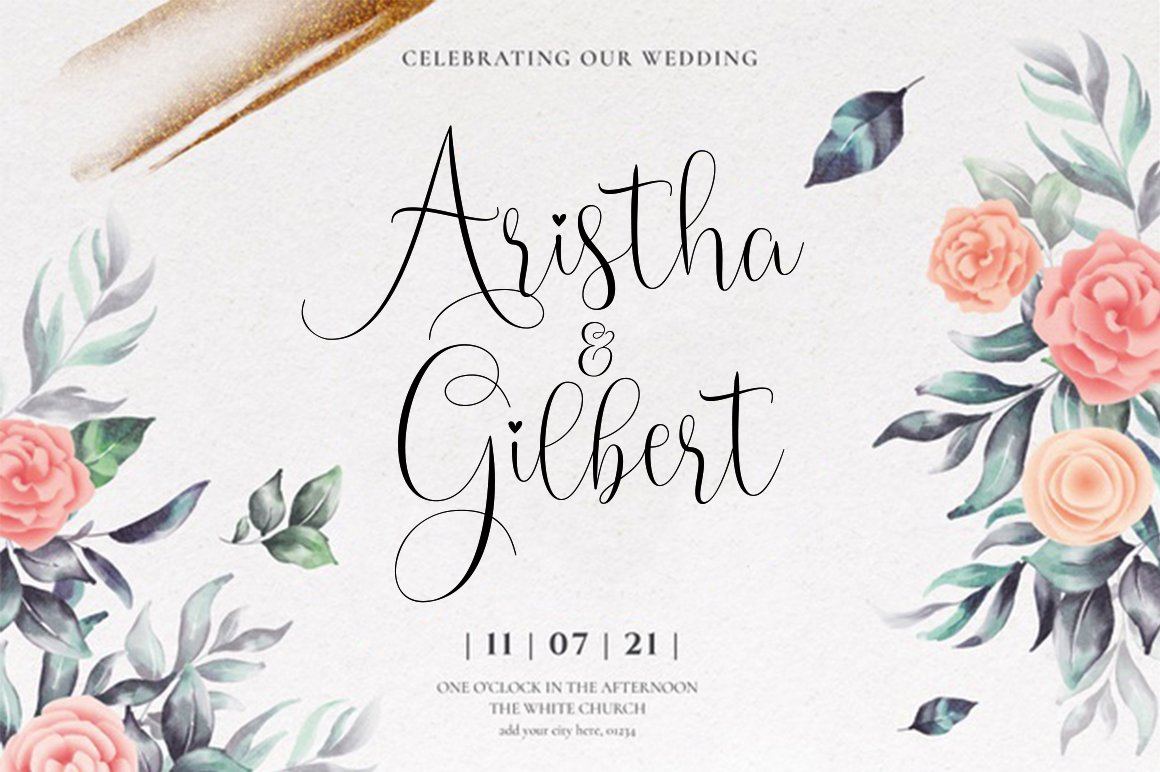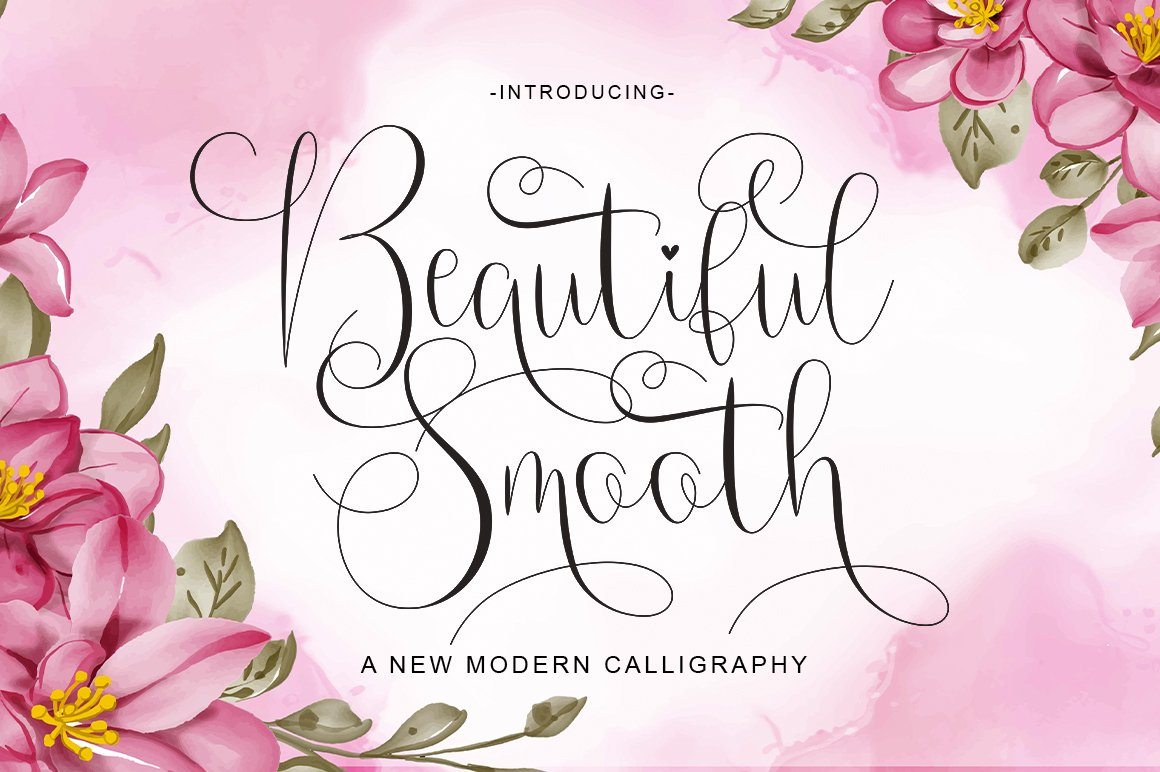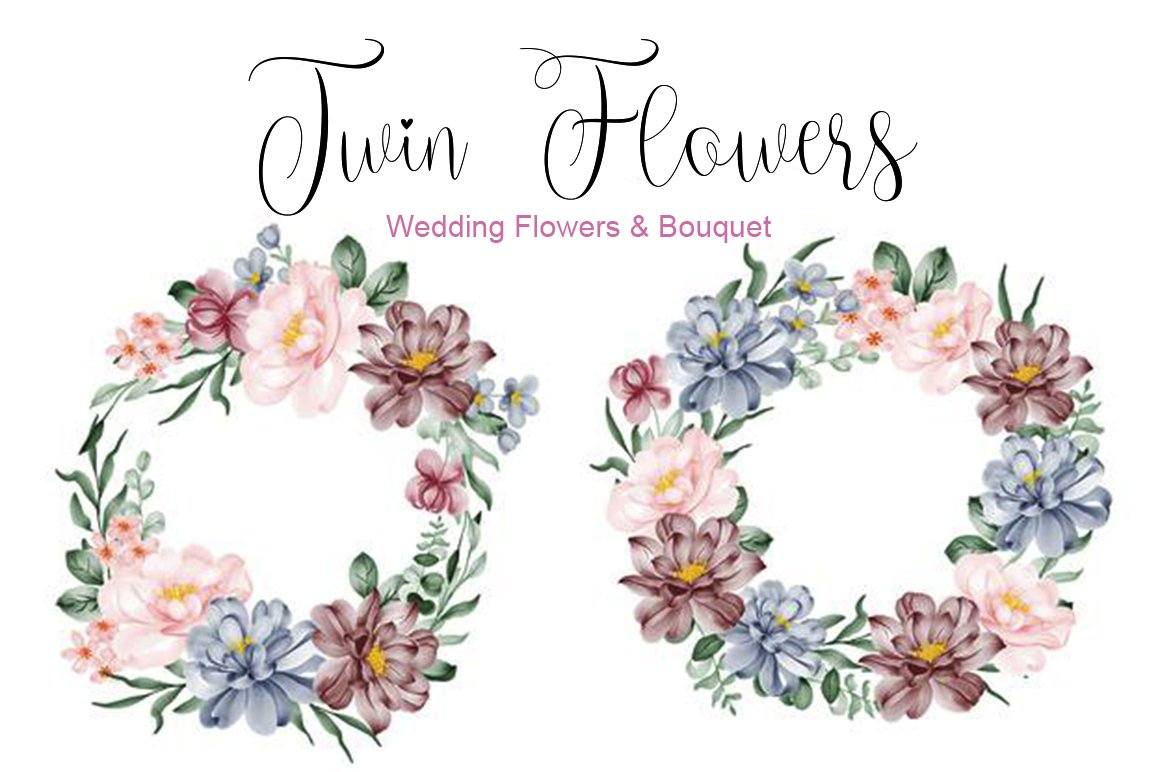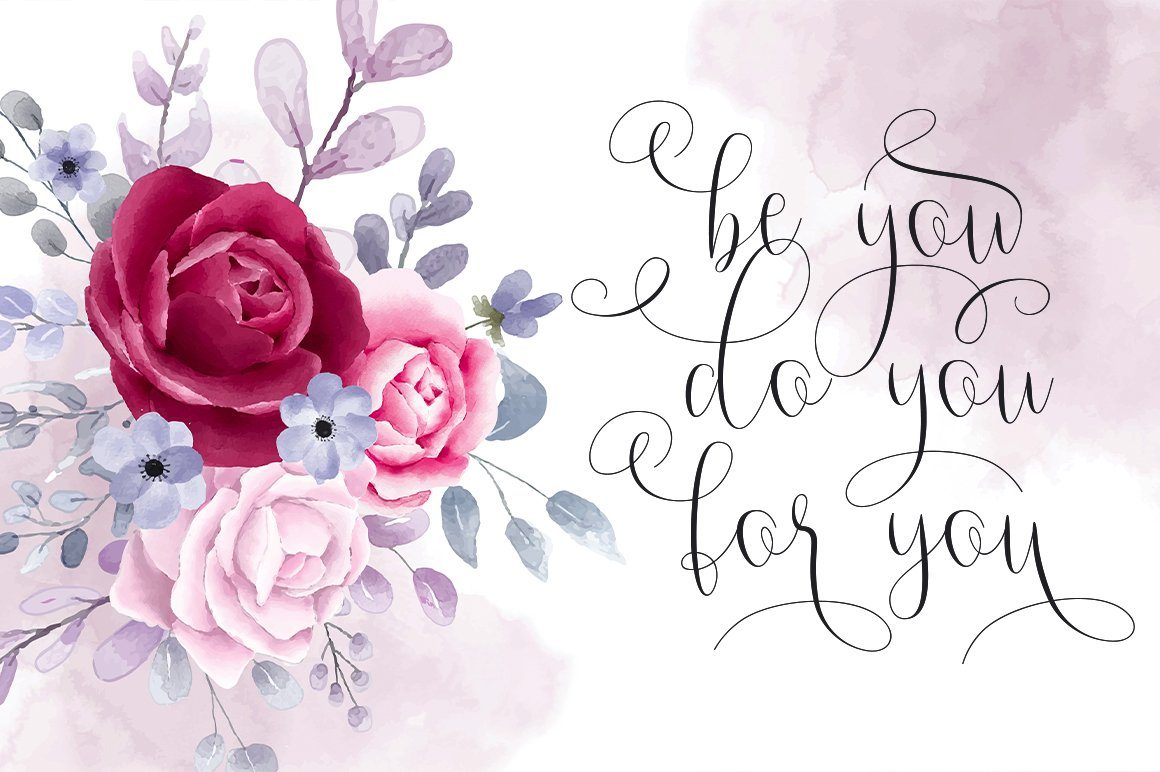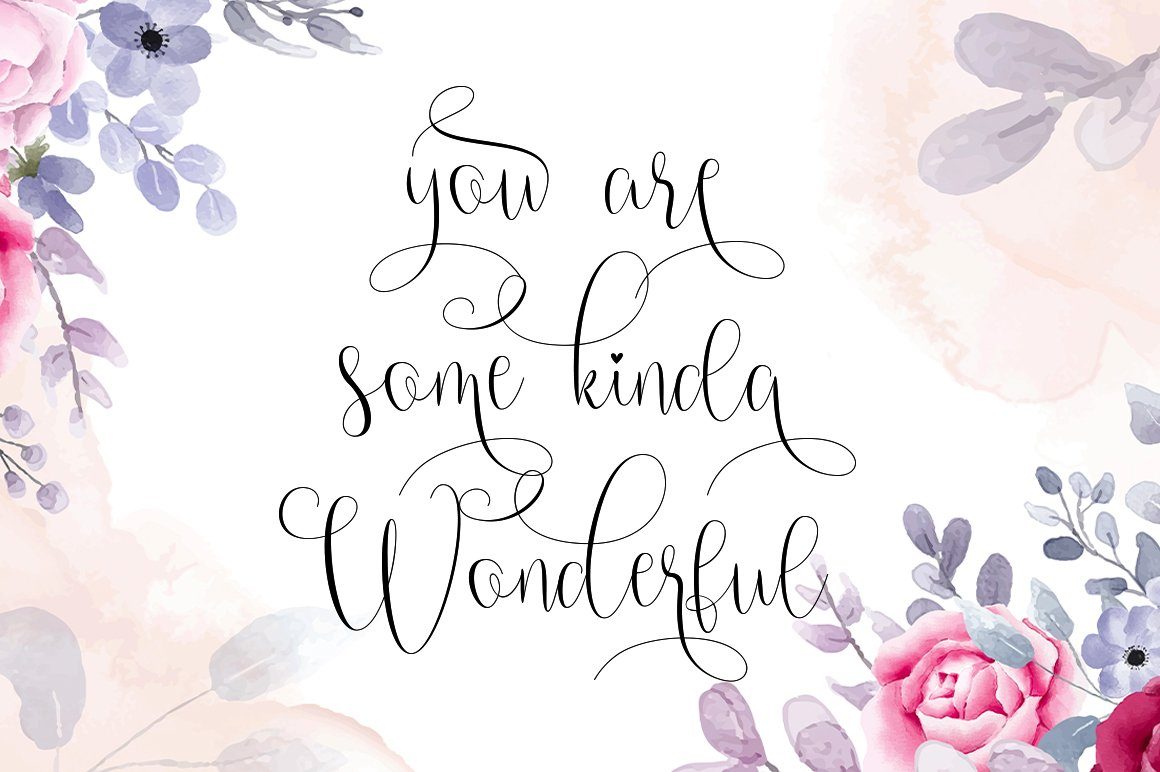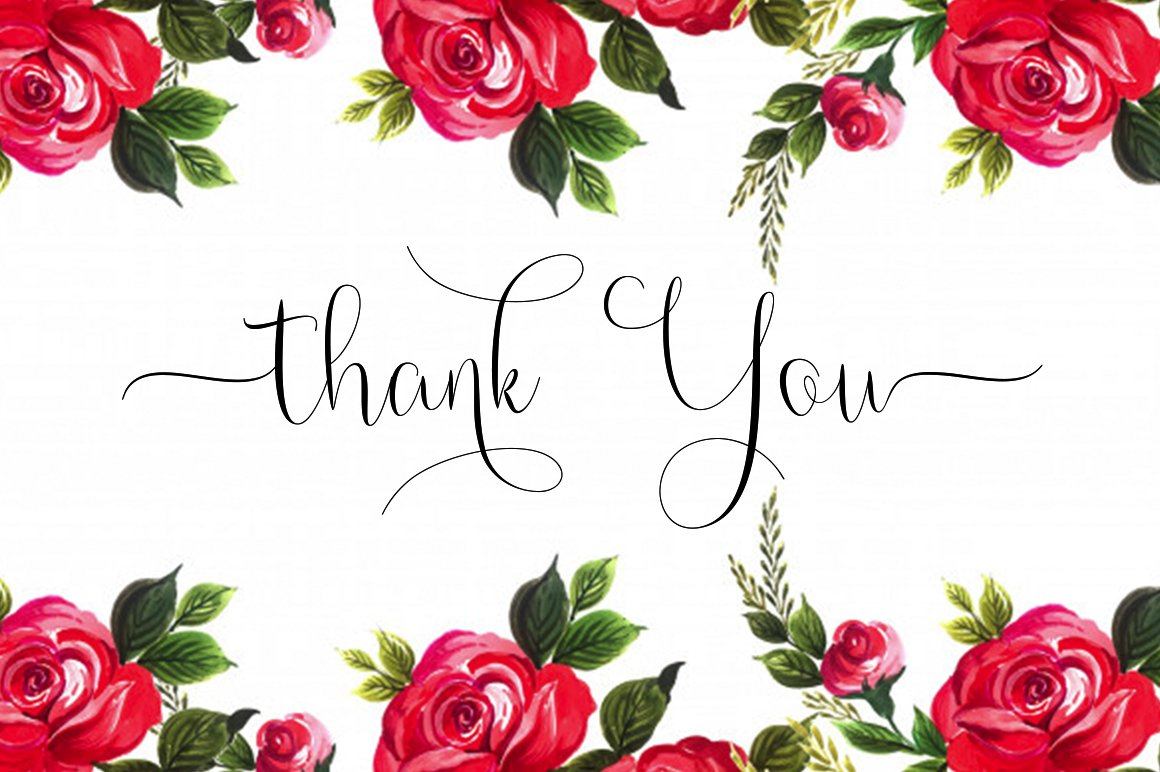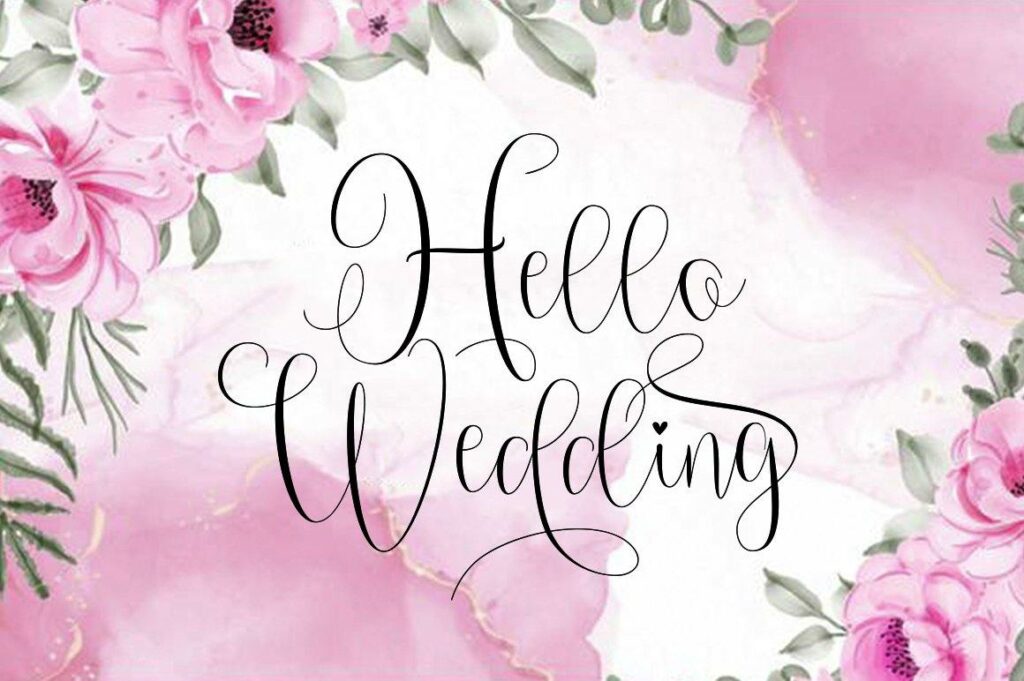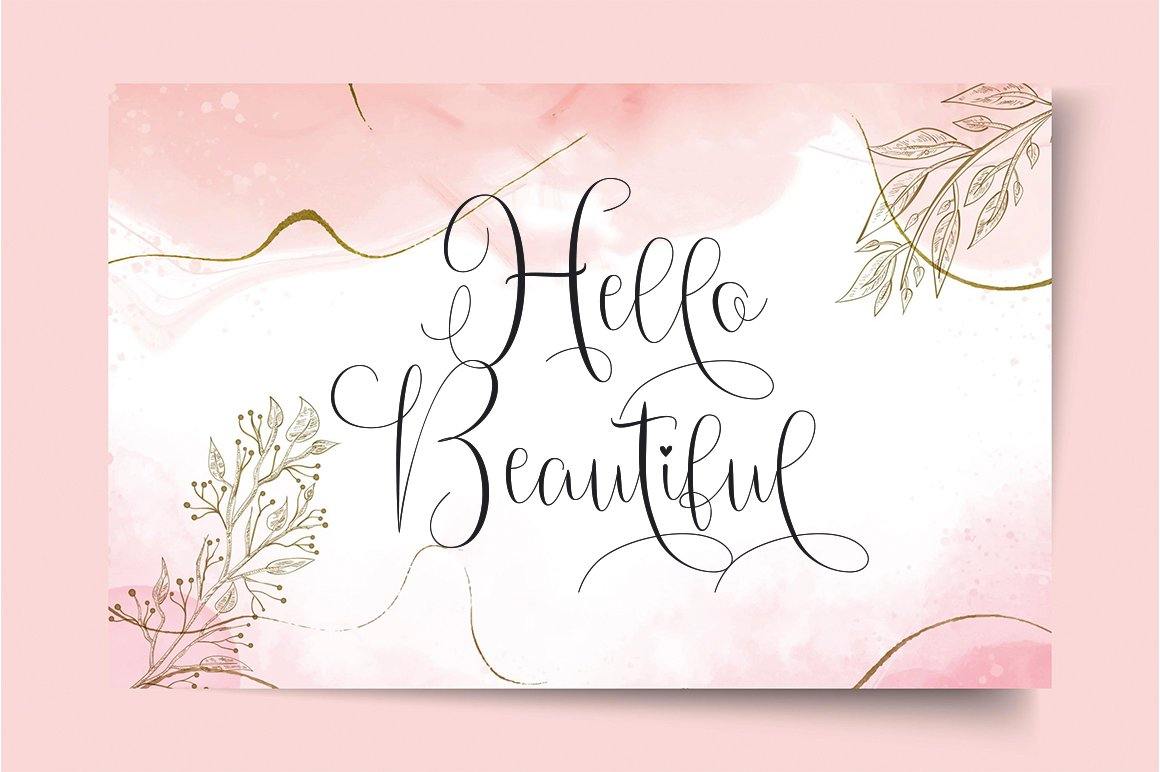
Beautiful Smooth
About Beautiful Smooth
Beautiful Smooth adalah font tulisan tangan ringan yang indah dengan nuansa unik dan dampak yang menakjubkan. Ini akan menambahkan percikan mewah ke proyek desain apa pun yang ingin Anda buat! Font ini dikodekan PUA yang berarti Anda dapat mengakses semua mesin terbang dan ligatur yang menakjubkan dengan mudah!